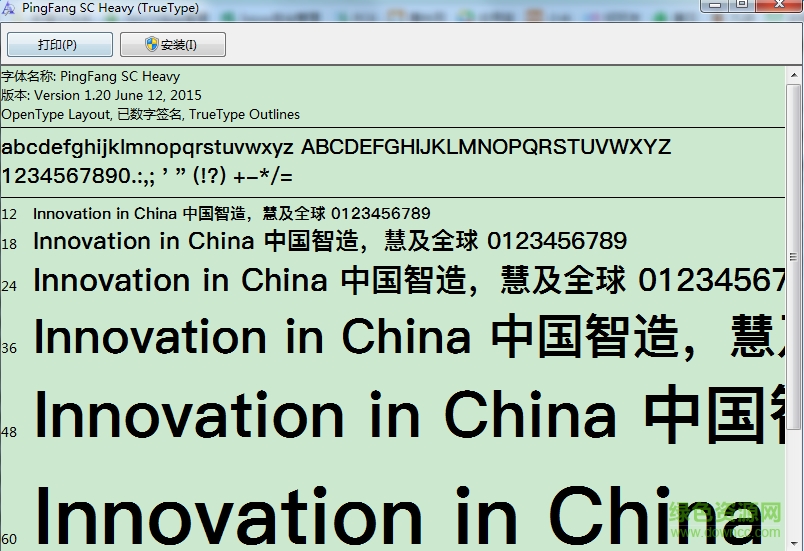
pingfang sc heavy
pingfang sc heavy字体是一款经典的英文字体,这款字体笔画粗壮,字形端正大方,整体效果非常出色,适用于广告设计、排版印刷等领域。喜欢这款字体的朋友欢迎来绿色资源网免费下载使用。
pingfang sc heavy字体效果展示
pingfang sc heavy字体